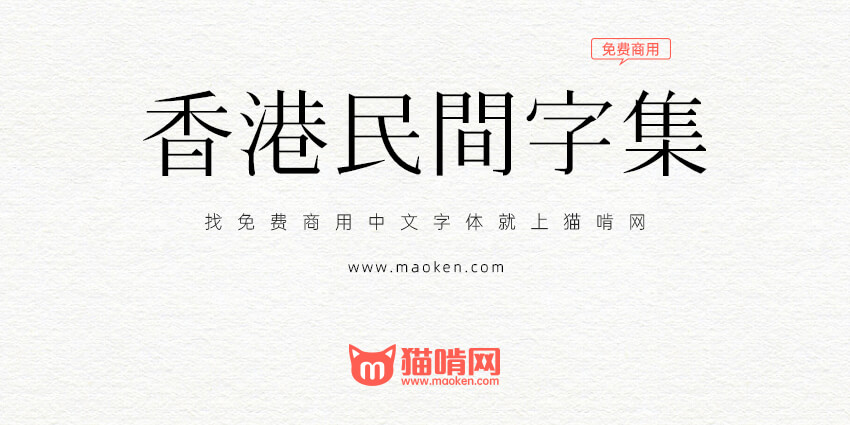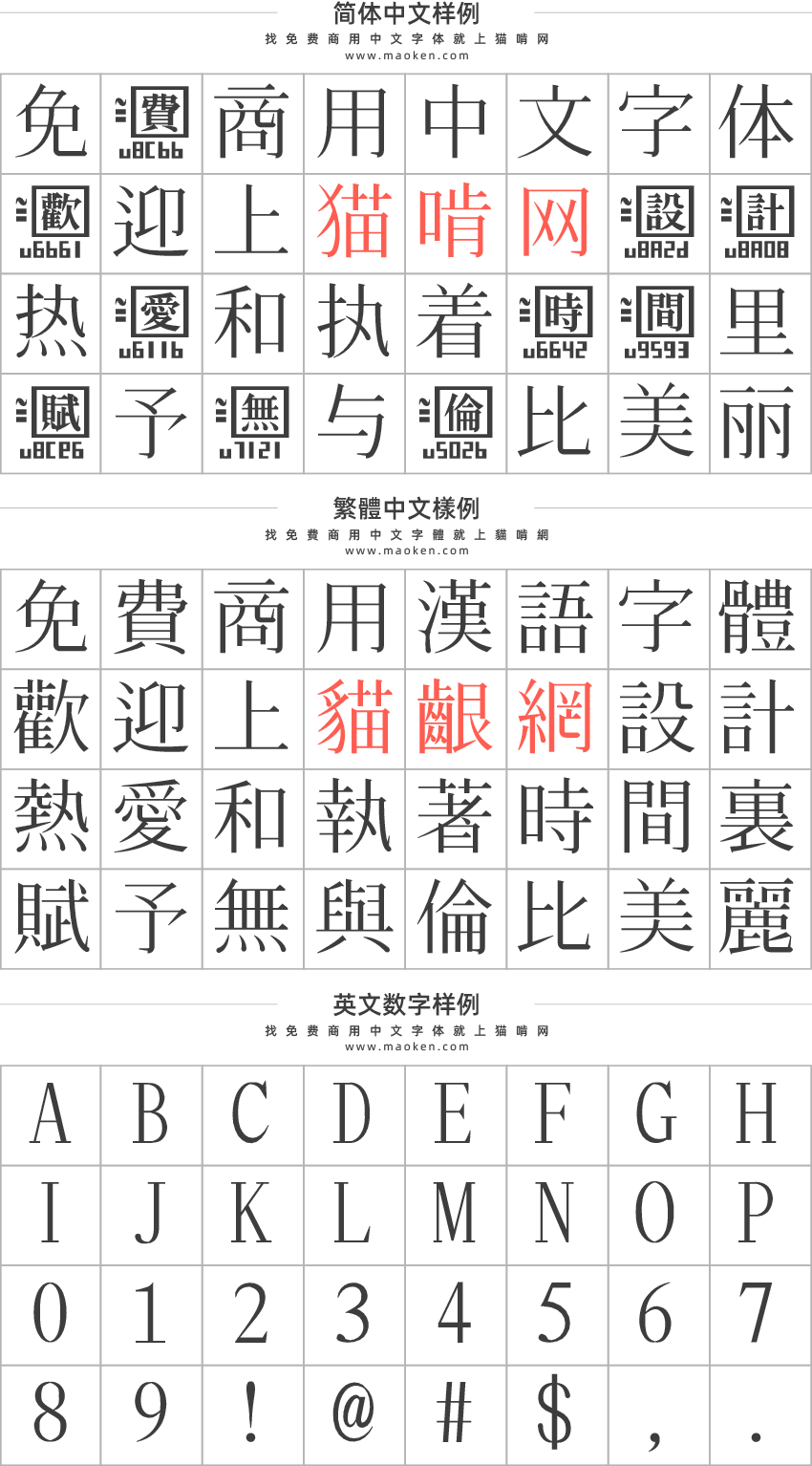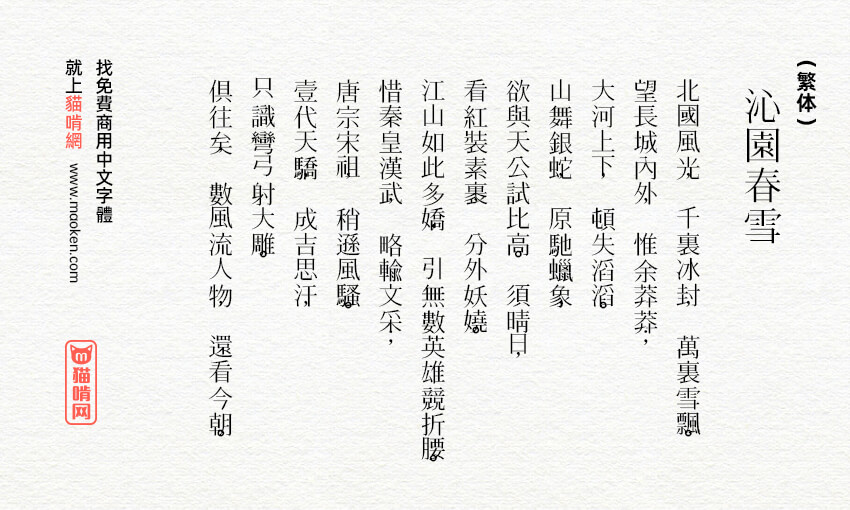
香港民间字集:在明代字体中创建现代和历史汉字字体
字体作者:Henry Chan (中国香港) 字体字重:1个
香港民间字集(HKCS)是一项在明代字体中创建现代和历史汉字字体目录的项目。这是一种支持传统正字法的衬线字体,它是由@SyaoanHinata所勾画的。传统的正字法是比较适合现代甲骨文、青铜铭文和小印章词源研究的。此版本的字体包括Uro/Uro+中的所有字符,并从分机A/B中选择字符,以便在香港支持粤语。
原版的标点符号的行高有点问题,本站热心网友“猫啃新人”把字符的行高问题进行了修正,十分感谢!
不過窗的囪為什麼是台灣字形?
• 囪小篆就是那麼寫得
这个字体竖版排列标点符号似乎有问题呀~~
• 这个字体的标点符号行距好像是有点问题的,但他们好像不维护了